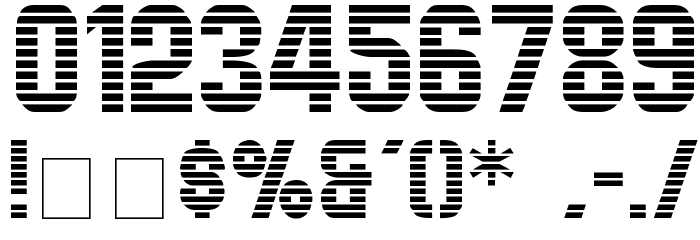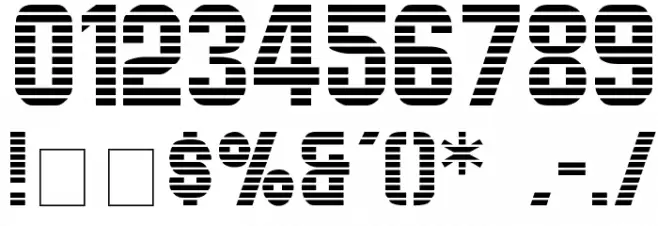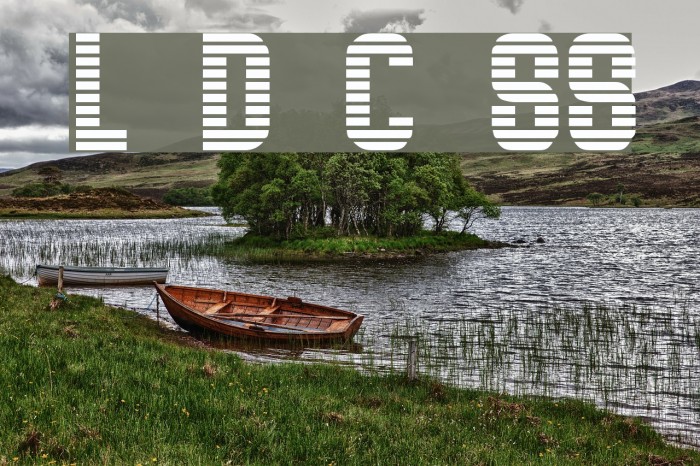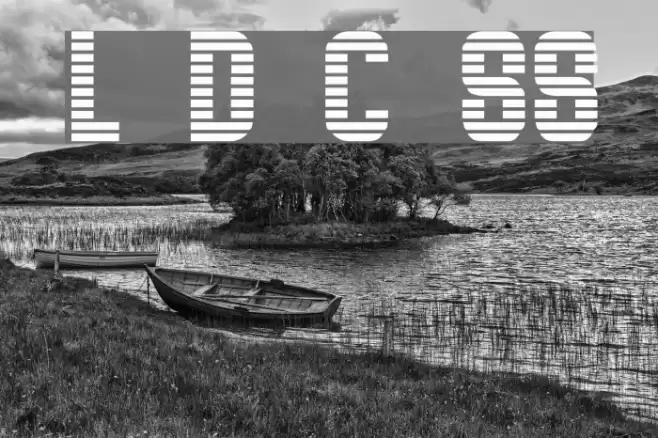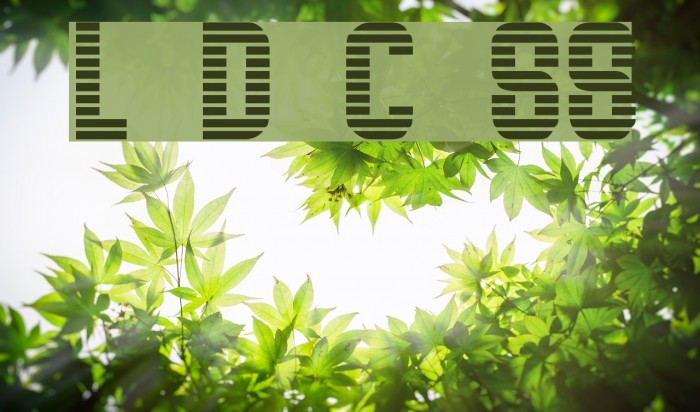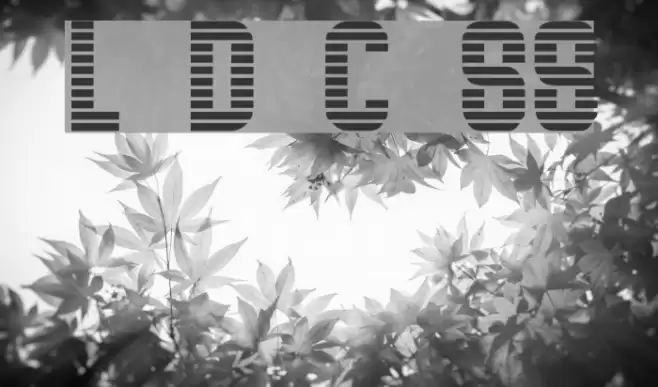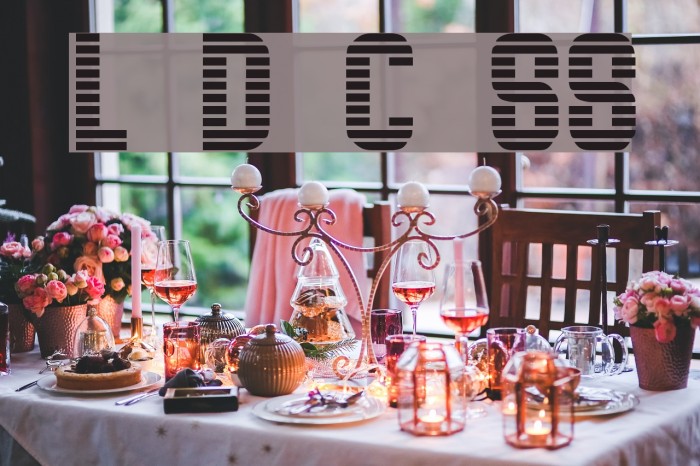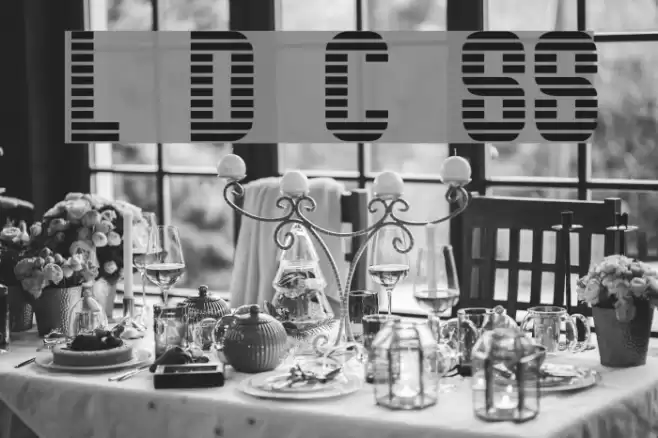
Levelor Display Caps SSi Font
| समग्र शैली | Modern, Decorative |
| उपयोग का मामला | Headlines, Logos, Posters |
| सुझाए गए प्रोजेक्ट | This font is perfect for poster designs, branding materials, and any project that requires a bold, attention-grabbing headline or title. |